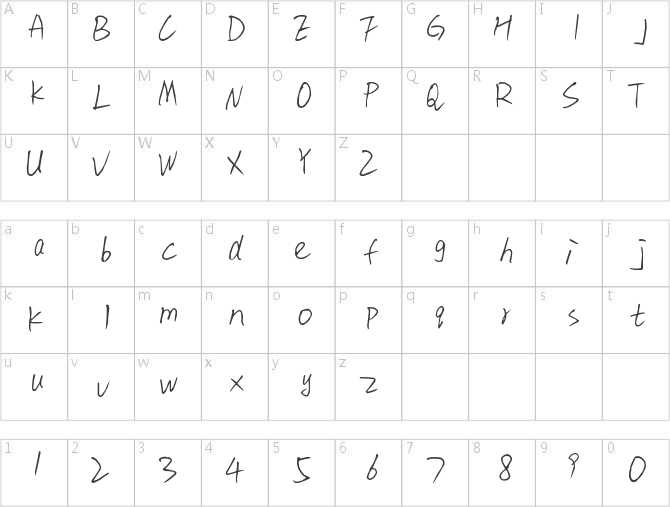
BoLeBaoZaoti 詳情頁
字體名稱: BoLeBao
BoLeBaoZaoti
BoLeBaoZaoti介紹
BoLeBaoZaoti字體字庫是一款讓人賞心悅目、百看不厭的英文字體,適合各類廣告和產品包裝設計應用,字體大小3.31MB,格式為ttf字體,上傳用戶是文生電腦,作者/版權方為未知